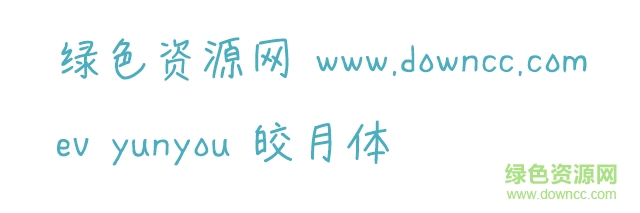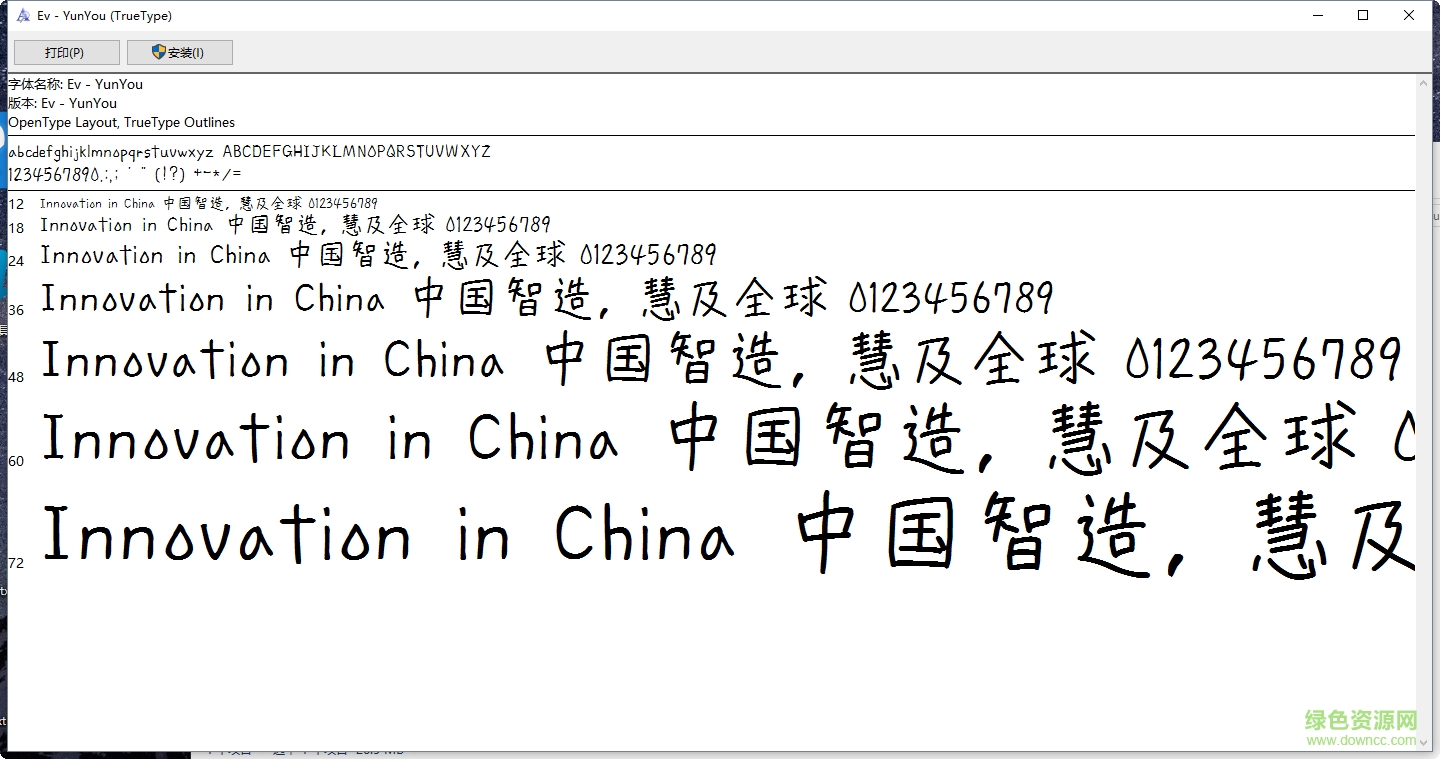
ev yunyou字體即皎月體字體,這款字體非常適合用于海報(bào)或是日常生活中。歡迎感興趣的小伙伴來(lái)綠色資源網(wǎng)下載!
ev yunyou字體,中文名稱(chēng)叫做皎月體字體,是一款非常實(shí)用的中文字體,該字體線(xiàn)條比較纖細(xì),字體呈卡通風(fēng)格,整體效果非常的出色,并且字庫(kù)完整,可用于藝術(shù)設(shè)計(jì)、包裝印刷、簽名設(shè)計(jì)、圖形設(shè)計(jì)等領(lǐng)域
輕松活潑,優(yōu)雅簡(jiǎn)潔